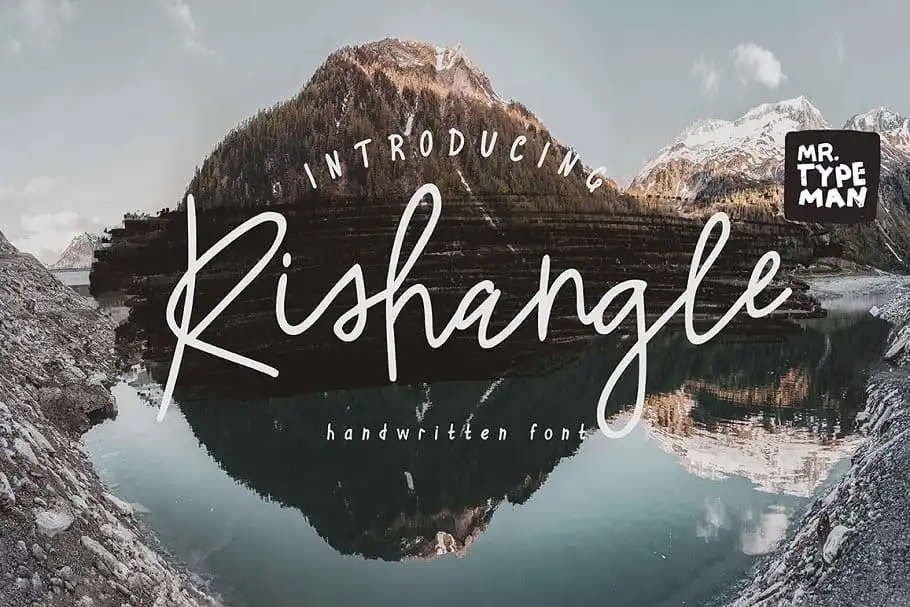
A Rishangle Handwritten Font é uma beleza natural que brota direto das mãos humanas. Ela traz a essência dos traços reais, adicionando ligaturas únicas e alternativas para criar um estilo de assinatura perfeito. Esta fonte Script não apenas oferece letras maiúsculas e minúsculas, mas também pontuação padrão, números e letras especiais que se adequam a uma ampla gama de idiomas europeus. Perfeita tanto para fotografias, fundos de água, postagens nas redes sociais, anúncios, logotipos & marcações, convites, designs de produto, etiquetas, papelaria e até mesmo para as embalagens de produtos, a Rishangle é uma escolha ótima para quem procura uma fonte escrita à mão que transmite um toque autêntico. Seja você criando uma identidade visual ou adicionando um toque único em qualquer projeto editorial, a Rishangle oferece uma experiência de uso fluida e extremamente natural, criando um impacto imediato e memorável.